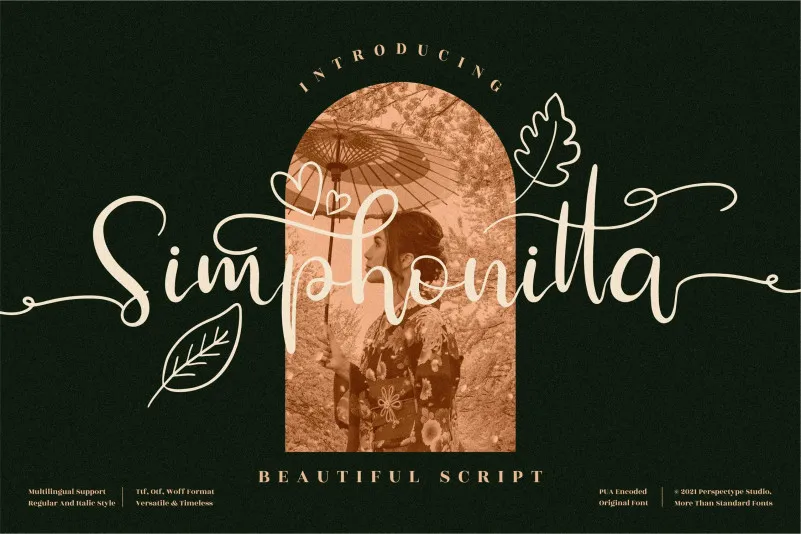
A Simphonitta é uma elegante tipografia script que chama atenção por sua sofisticação moderna. Seu design refinado pode ser utilizado para diversas finalidades, desde identificações de marca e convites até postagens no Instagram e anúncios de casamentos. A fonte inclui um PUA (Unicode Private Use Area) que permite a fácil acesso aos todos os elementos gráficos e swashes, tornando o processo de criação de designs incrivelmente conveniente. Numa era em que a personalização digital está em alta, a Simphonitta é uma opção perfeita para qualquer projeto que valoriza a precisão e a elegância na tipografia.